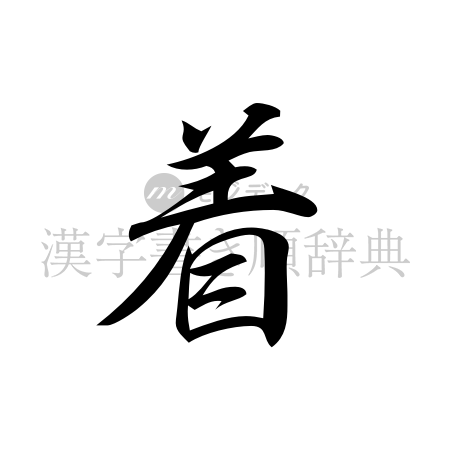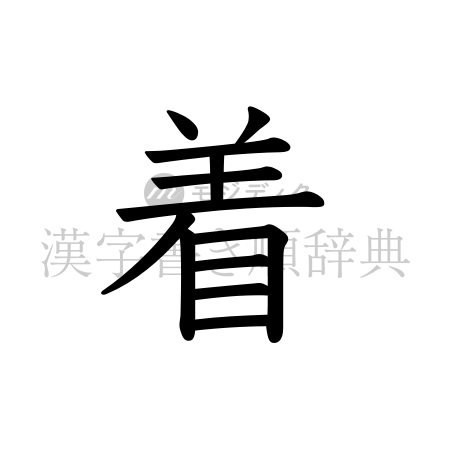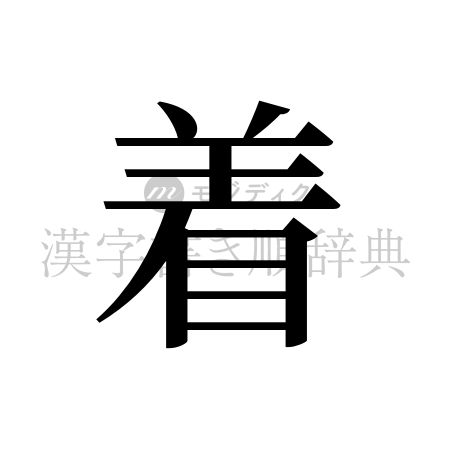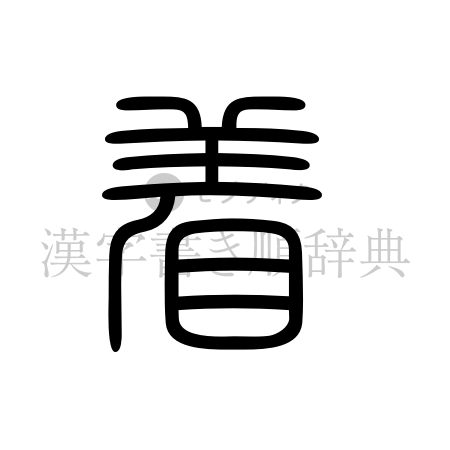
漢字「着」(チャク)の書き順・読み方・意味・部首・画数
「着」の書き順動画アニメーション(12画)
「着」の読み・画数の基本情報
「着」の書体
「着」の意味
- 衣服を身につけること。
- 到達すること。
- ある状態になること。
- 注意を向けること。
- 物事が始まること。
- 位置を占めること。
- ある場所に定着すること。
- 物事が確定すること。
「着」の意味の英訳
漢字は1文字で多様な意味を持ちますが、「着」を英語で表す場合、一般的には don, arrive, wear, counter for suits of clothing などがあります。
「着」の成り立ち・由来
| 構造 | 「著」の変形。もとは意符艸+音符者 |
「着」は「著」の異体字(俗字)から生まれた字です。もとの「著」は、意符の艸(くさかんむり)に音符の「者」を組み合わせた形声文字で、「あらわれる・つく」といった意味をもちました。この「著」の字形が崩れ、簡略化される過程で「着」という形が生じ、やがて「つく・きる・到達する」の意味を担う字として独立しました。現在の字は羊・目などの形を含むように見えますが、これは変形の結果であって、もとの成り立ちとは直接関係しません。日本では衣服を身につける・ある場所に到達する意で広く用いられます。
※ 羊・目などの構成部品は字形変化の結果であり、本来の字源とは無関係です。
「着」は名前に使える漢字です。